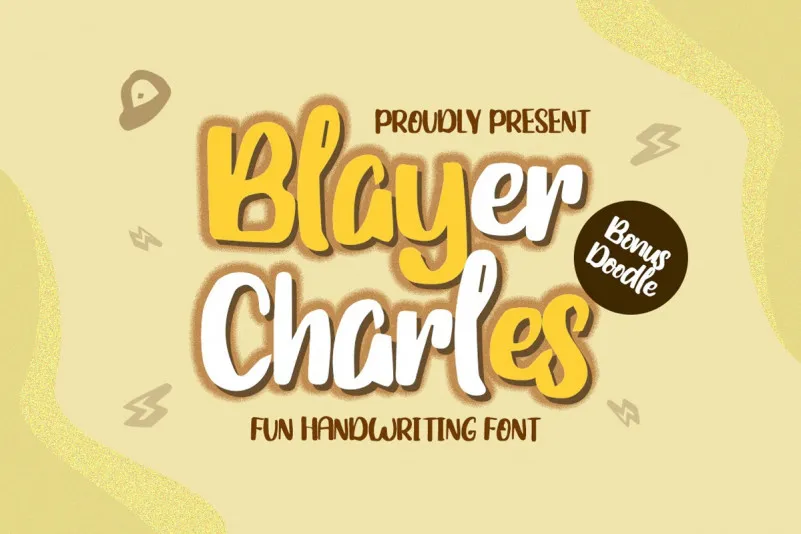
Blayer Charles – Playful Font – Download Grátis
Olá pessoal, aqui está uma bela fonte script chamada Blayer Charles Playful Font. Esta é uma nova adição para sua coleção de fonts, especialmente criada para tornar seus projetos gráficos ainda mais animados e alegres. Com um toque leve de brincadeira e fantasia, esta font é perfeitamente adequada para aplicar em suas criações de arte, logos, embalagens de produtos, design de casamento, posts nas redes sociais e anúncios. Se você está procurando por uma maneira divertida de dar um toque único a seus designs, Blayer Charles Playful Font é a escolha certa. Suas linhas curvilíneas dançantes criam um charme mágico que se torna perfeito para estilos como branding, design de logomarca, criação de cartões de convite e até mesmo em editoriais de casamento. Seja para o seu próximo projeto de fotografia ou criação de watermark, ela certamente enriquecerá suas criações. Em resumo, Blayer Charles Playful Font é uma adição encantadora ao seu acervo de fontes que garantirá um toque único e divertido a qualquer design. Está pronto para se inspirar no encanto de sua forma mágica? Não perca tempo, tente esta nova font!